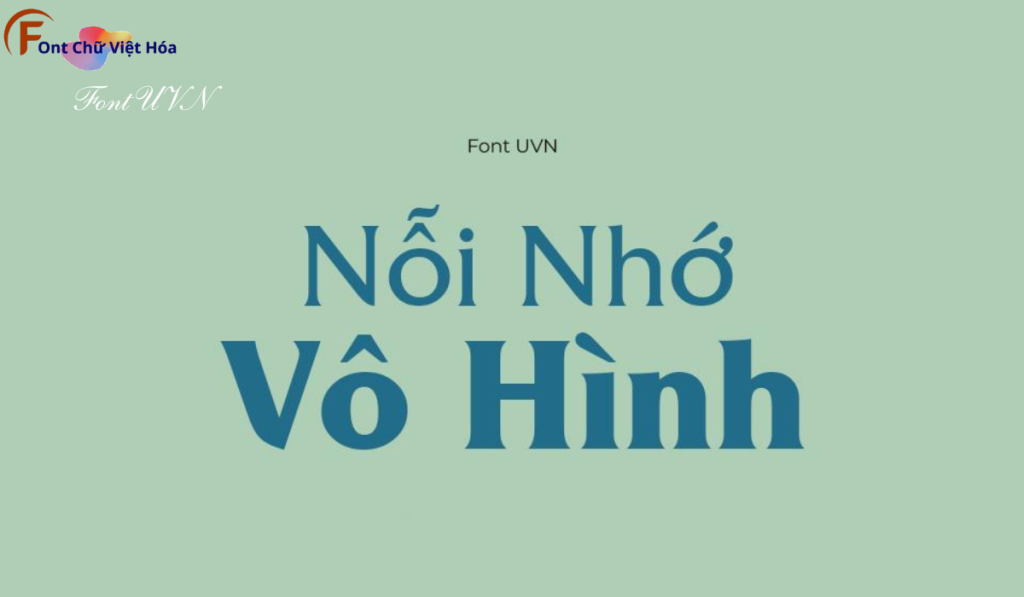
Font Chữ UVN Lạc Long Quân Việt Hóa
Tác giả: UVN Lạc Long Quân
Bộ Font: UVN
Phân loại: Cá tính, Mạnh mẽ
Kiểu chữ: Có chân
Độ dày: Đậm, Thường
Font Chữ UVN Lạc Long Quân Việt Hóa là một font chữ có chân hiện đại, thuộc bộ font UVN. Được thiết kế với mục tiêu mang lại sự tinh tế và thanh lịch, font này phù hợp cho các dự án thiết kế như website, tài liệu, và bao bì sản phẩm. Với các nét chữ rõ ràng và độ dày đều đặn, Font Chữ UVN Lạc Long Quân Việt Hóa không chỉ dễ đọc mà còn tạo cảm giác chuyên nghiệp. Việc Việt hóa font giúp người dùng dễ dàng sử dụng trong các thiết kế tiếng Việt, mang lại sự tiện lợi và thẩm mỹ cao.